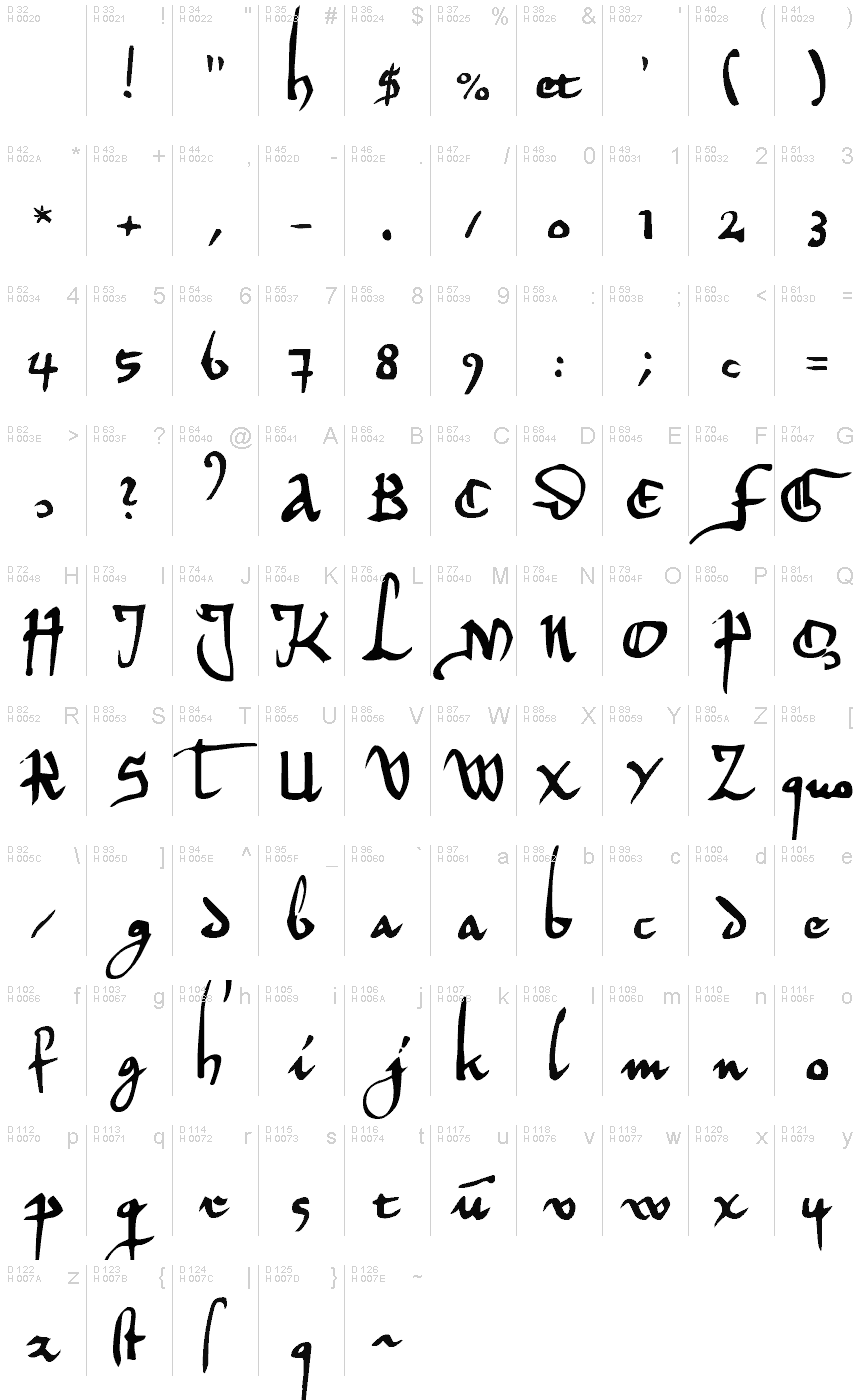
Herman Decanus AH von Andreas Höfeld ist eine kostenlose, handgeschriebene Script-Schrift mit einem mutigen, tintenreichen Charakter. Die Striche wirken, als wären sie mit einem voll getränkten Pinsel gemalt – dick, leicht rau und voller Dynamik. Sie verleihen jedem Wort eine laute, selbstbewusste Stimme, ohne dabei in Chaos zu verfallen. Die Buchstaben neigen sich in einem lockeren Rhythmus nach vorne, was die Lesbarkeit bewahrt und gleichzeitig wild und ausdrucksstark wirkt.
Mit Herman Decanus AH erhalten Sie ein Schriftbild, das sich wie eine Signatur mit einem feuchten Marker anfühlt und nicht wie saubere Schulschrift. Es glänzt auf Plakaten, Albumcovern, rebellischem Branding, Zines, Event-Flyern und auffälligen Social-Media-Grafiken. Diese kostenlose Schrift funktioniert besonders gut, wenn Sie sie groß setzen und mit einer sauberen, ruhigen serifenlosen Schrift kombinieren, damit ihre dunklen, stämmigen Kurven richtig zur Geltung kommen.
Herman Decanus AH
Andreas Höfeld
Herman Decanus: nach einer Urkunde aus dem 13. Jahrhundert, sogenannte Kanzleischrift, geschrieben von Dekan Hermann zu Soest, 1269. Diese Schrift zeichnet sich durch große Ober- und Unterlängen aus und eignet sich besonders für historisch wirkende Urkunden und Dokumente. Nichts für Leute mit Leseproblemen oder um viel Text auf einer Seite unterzubringen.
Die Schrift existiert in zwei Gewichten: normal und light.